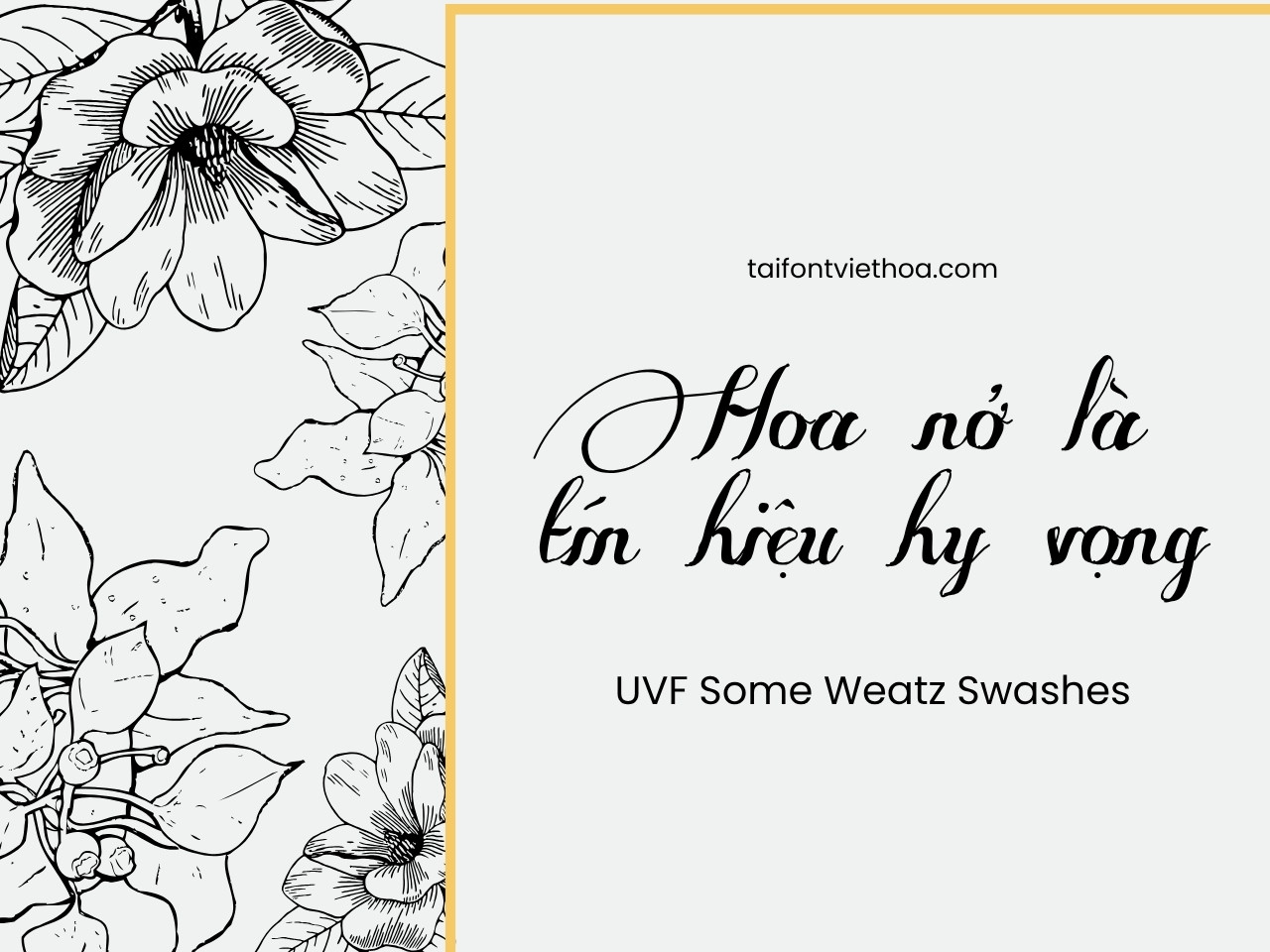
Giới thiệu về font UVF Some Weatz Swashes
UVF Some Weatz Swashes là phiên bản đặc biệt mở rộng của font “Some Weatz”, một kiểu chữ script nổi bật với các đường cong mượt mà và phong cách viết tay cổ điển. Font gốc được phát triển bởi Måns Grebäck – một trong những nhà thiết kế nổi tiếng trong lĩnh vực typography calligraphy. Phiên bản “Swashes” bổ sung hàng loạt các đuôi chữ cách điệu, mang lại khả năng tùy biến cao và tạo điểm nhấn nghệ thuật cho từng dòng chữ. Font hỗ trợ hơn 200 ngôn ngữ, trong đó bao gồm tiếng Việt, các ngôn ngữ Latinh mở rộng, và nhiều ký tự đặc biệt phục vụ thiết kế đa dạng.
Đặc điểm thiết kế và ứng dụng của UVF Some Weatz Swashes
UVF Some Weatz Swashes có cấu trúc chữ đậm vừa, nét bút tròn trịa và mượt mà, kết hợp cùng các đuôi swash dài và tinh tế giúp tăng chiều sâu thẩm mỹ. Font cung cấp nhiều ligature, ký tự thay thế stylistic và các glyph mở rộng, tạo điều kiện cho người dùng dễ dàng cá nhân hóa nội dung theo phong cách viết tay cổ điển hoặc lãng mạn.
Font đặc biệt phù hợp trong các thiết kế logo mỹ phẩm, thương hiệu cá nhân, thiệp cưới, thư mời, typography sáng tạo, bảng hiệu spa và bao bì cao cấp. Ngành nghề đề xuất: sự kiện – lễ cưới, làm đẹp, truyền thông nghệ thuật, thời trang cá tính và lĩnh vực quảng cáo cần thể hiện dấu ấn riêng.